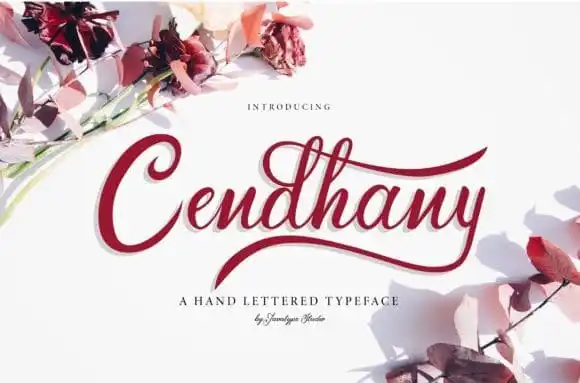
Cendhany Calligraphy Font – Download Grátis
A Cendhany Calligraphy Font é uma deliciosa mistura entre elegância e modernidade, nascida do trabalho natural de uma pena de caneta a mão. Esta fonte adquire um toque único, combinando elementos clássicos como o papel de prata com os truques criativos dos tempos atuais. Cada caractere é personalizado de forma harmoniosa e originalmente escrita à mão, permitindo que qualquer projeto em que seja aplicada tenha uma aparência sofisticada e diferenciada. O designer 99designs trouxe a esses caracteres um moderno enfeite, tornando esta fonte perfeitamente versátil para diversas aplicações. Seja para headlines, logotipos de marca, roupas de festa, embalagens, publicidade ou até mesmo para anúncios de casamento, a Cendhany Calligraphy Font está aqui para satisfazer os mais exigentes requisitos. Além disso, esta fonte oferece um extenso conjunto de recursos que inclui maiúsculas e minúsculas, pontuação, símbolos, números, alternativas de letras, ligaduras, e suporte a vários idiomas. Seja qualquer projeto gráfico que você está planejando, a Cendhany Calligraphy Font é uma escolha inteligente para adicionar um toque de elegância e individualidade à sua criação.